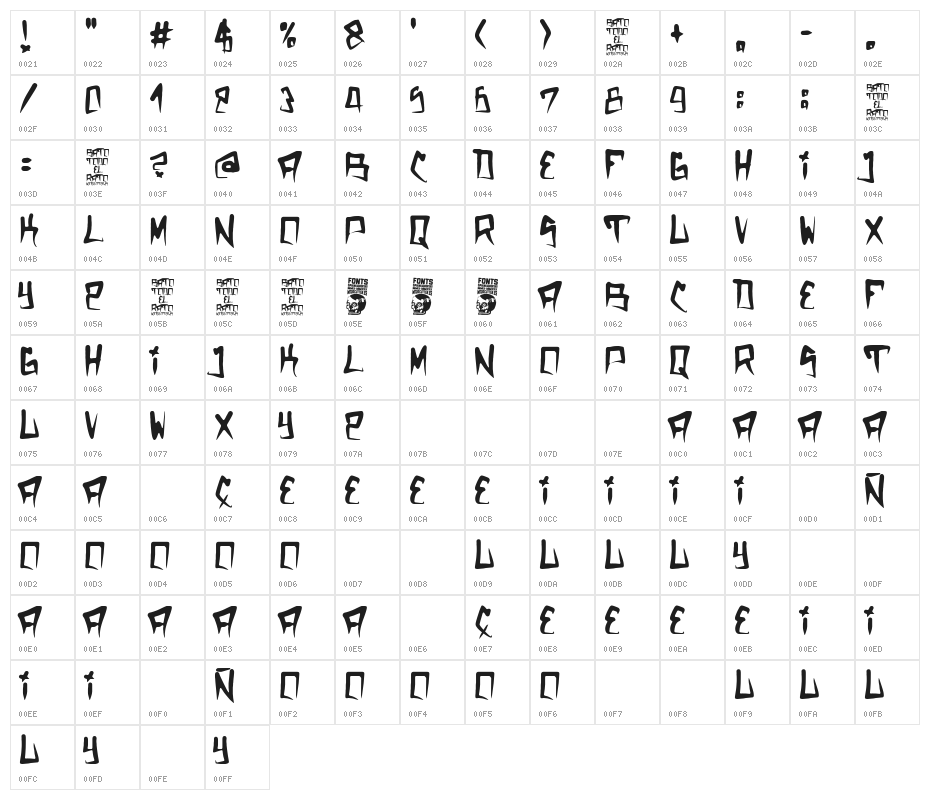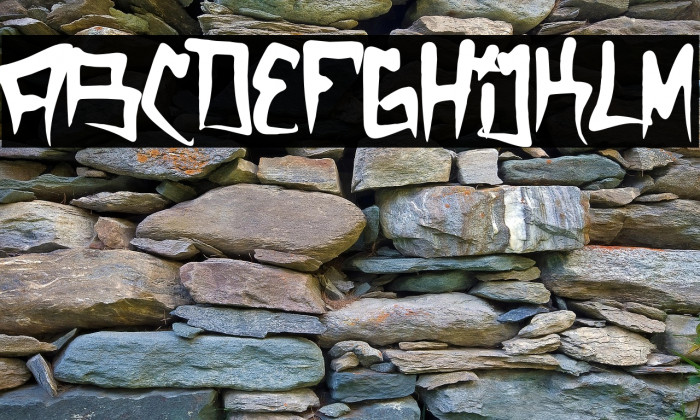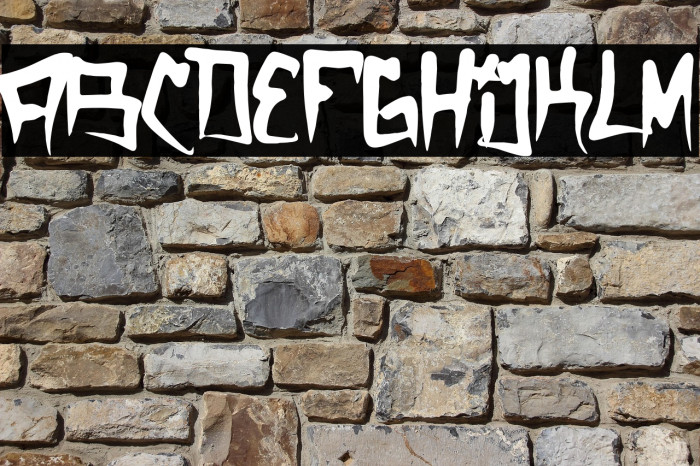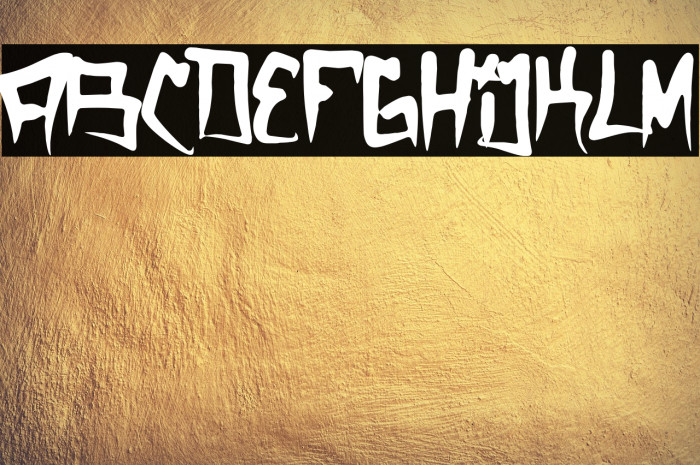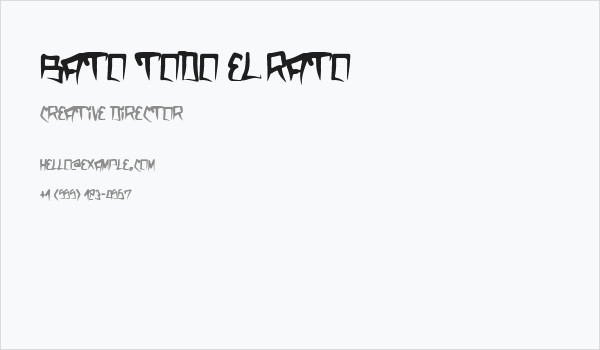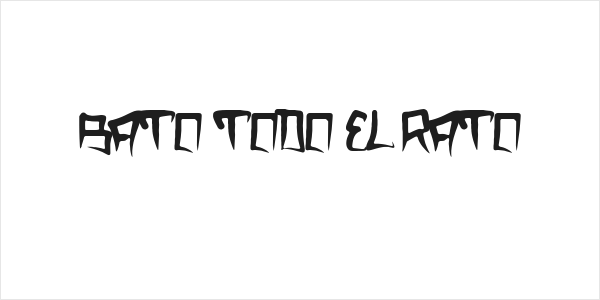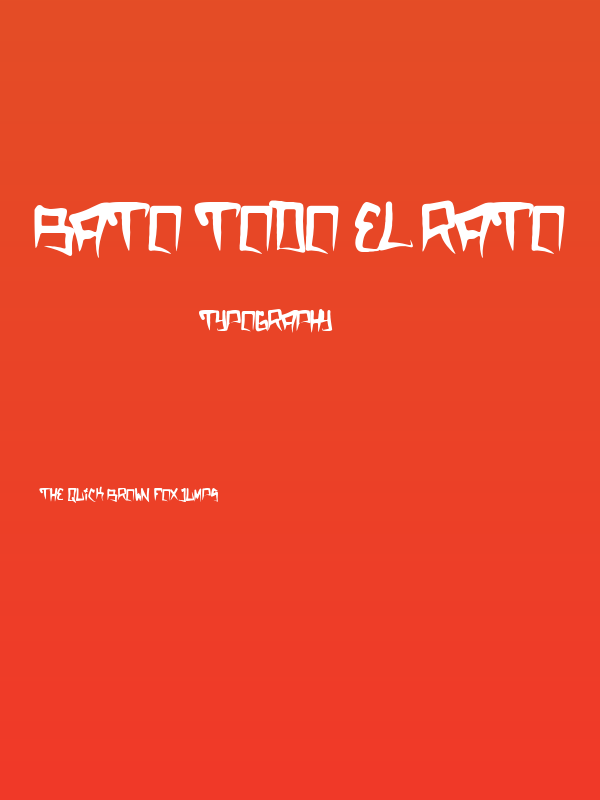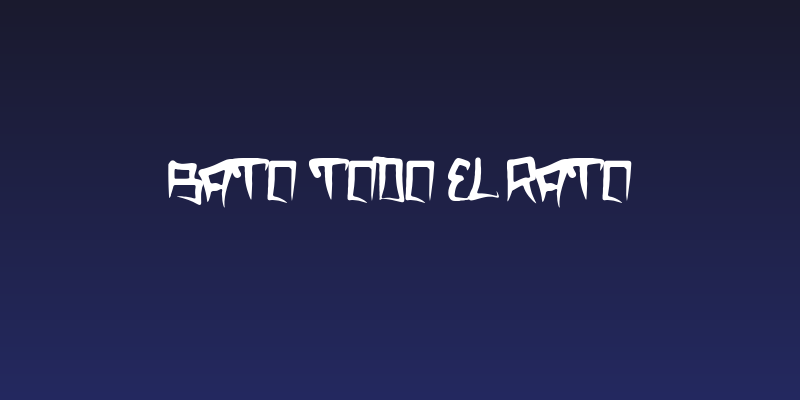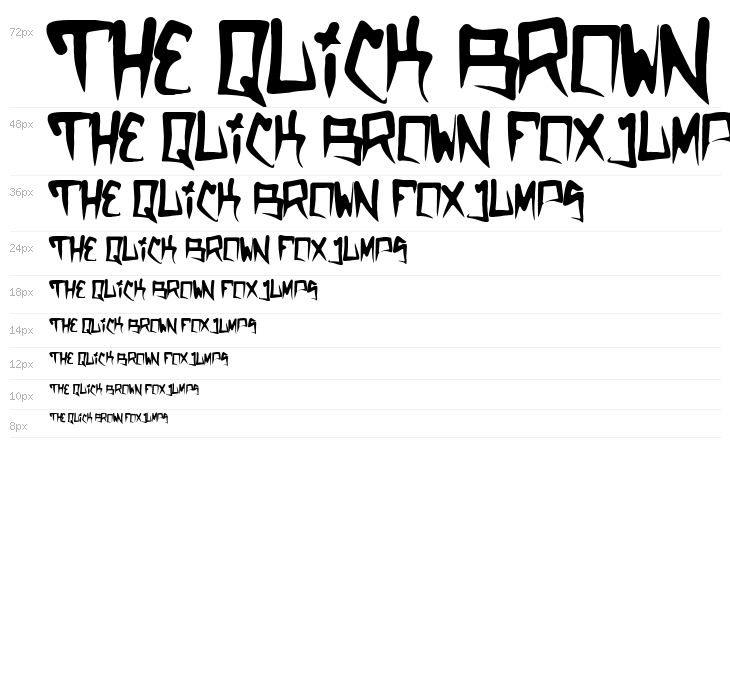
Bato todo el Rato Font
| Stile generale | Modern, Urban, Edgy |
| Progetti proposti | Ideal for street art designs, music album covers, urban-themed posters, and edgy branding projects. |